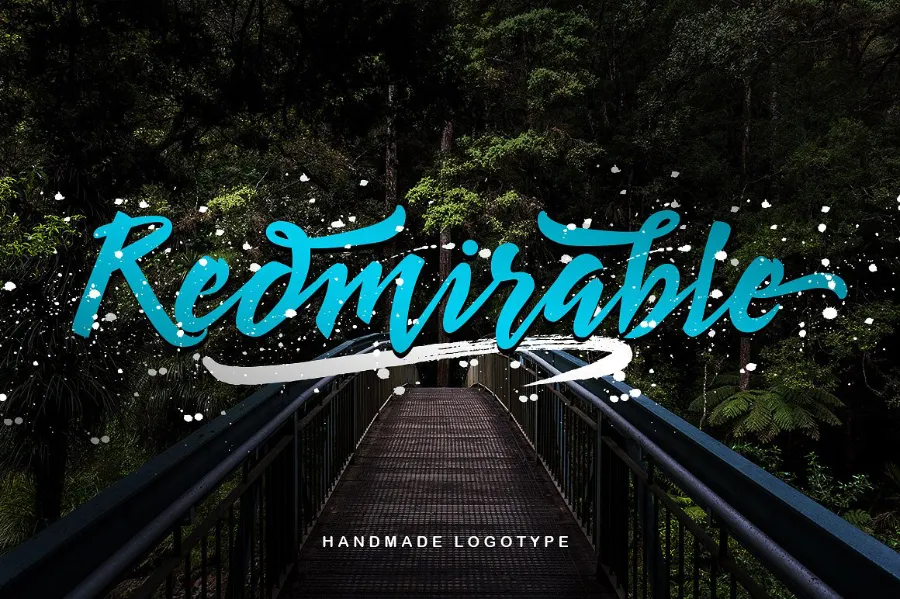
Redmirable Script Font – Download Grátis
Introduzimos a Redmirable Script Font! Esta é uma nova fonte para assinatura criada manualmente, com um estilo moderno e fresco e uma tipografia influenciada por calligrafia. Através de sua designação original e partilha pelo estúdio Putra Khan Studio, o Redmirable pode ser usado em uma variedade de formatos gráficos. Pode ser aplicado em materiais promocionais, logotipos, identidade visual, citações escritas à mão, embalagens de produtos, selos, anúncios, rótulos e até mesmo artigos publicitários. O Redmirable é perfeito para criar um design único, atraente e bem definido que irá impressionar seu público-alvo. Com sua modernidade sofisticada e estilo elegante, a Redmirável Script Font certamente será uma escolha excelente para seus projetos de branding.